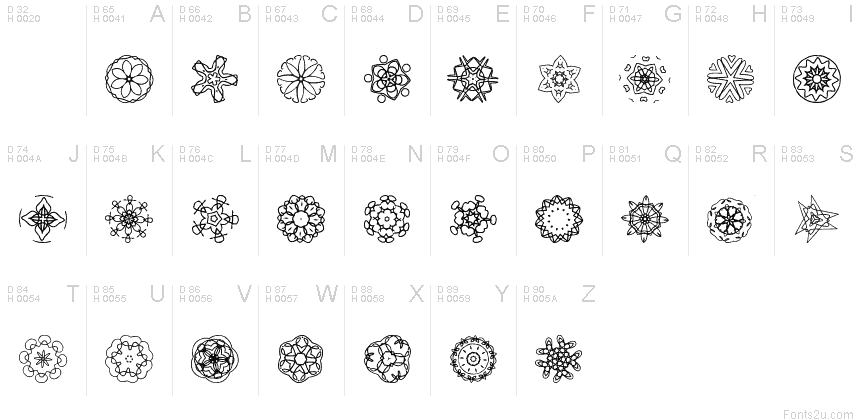
JI Kaleidoscope Bats 5
JI Kaleidoscope Bats 5 di Jeri Ingalls è un font dingbat decorativo gratuito. Ogni glifo è un mandala caleidoscopico disegnato a mano, con linee a inchiostro leggermente tremolanti che ricordano più gli schizzi di un taccuino che vettoriali sterili. Il mix di esplosioni circolari, stelle simili a fiocchi di neve e forme floreali specchiate ti offre istantaneamente ornamenti, bordi e icone senza dover passare ore a disegnarli tu stesso.
Con JI Kaleidoscope Bats 5 puoi decorare rapidamente inviti, fanzine, album, pagine da colorare, adesivi e post social con motivi intricati e ipnotici. Il tratto leggero e arioso fa sì che questi simboli si riproducano bene anche in piccole dimensioni, ma danno il meglio di sé quando vengono ingranditi come cornici o motivi di sfondo. Per gli abbinamenti tipografici, usa questo font gratuito con un semplice sans-serif per il testo, così le forme ornamentali rimarranno al centro della scena.